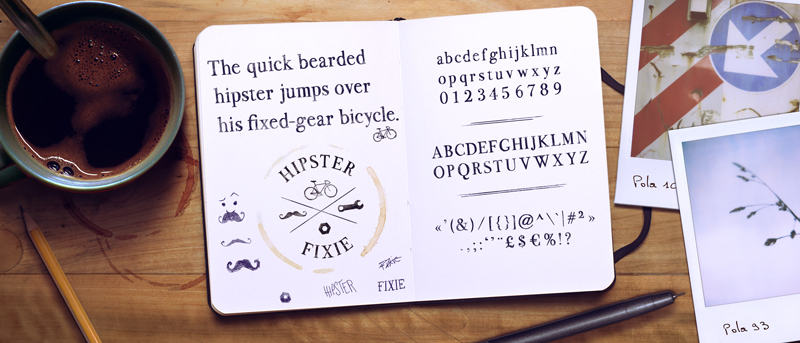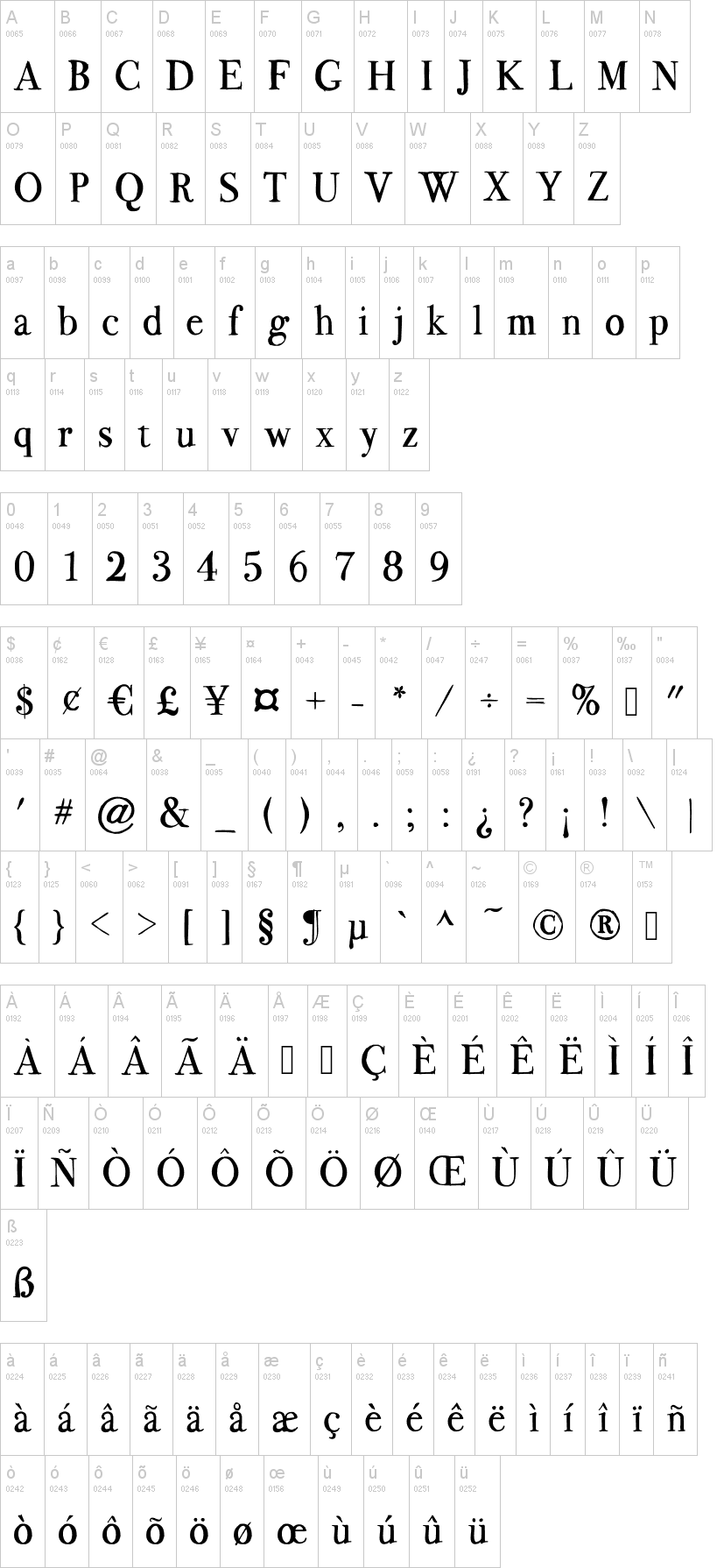
Note of the authorVoici une typographie à empattements avec un aspect manuel et irrégulier.
Elle est inspirée de la Bodoni et contient la plupart des accents et caractères spéciaux utilisés en français et en espagnol.
Here is a serif typeface with a manual and irregular appearance.
It's inspired on Bodoni and contains most of the accents and special characters used in French and Spanish.